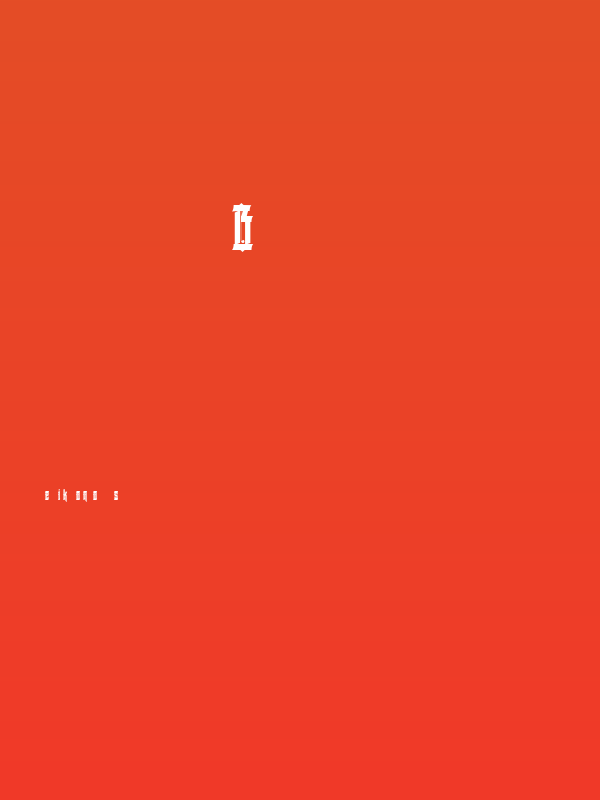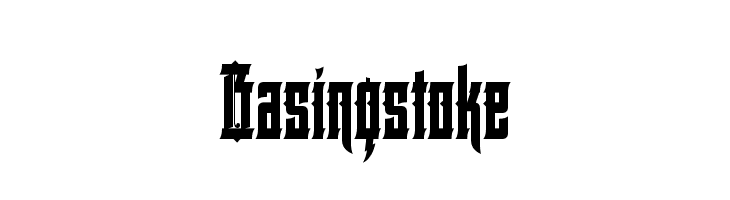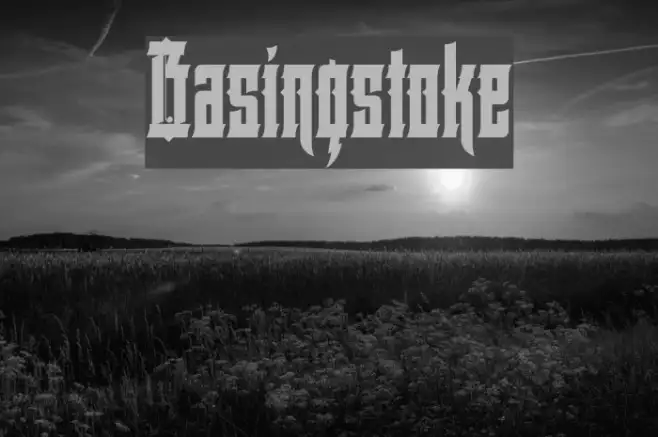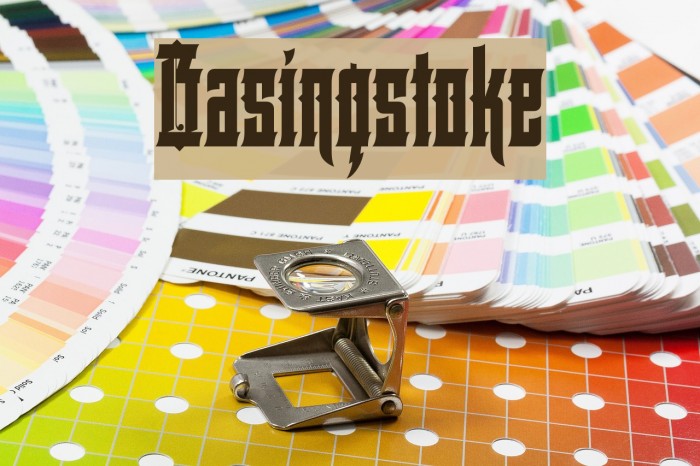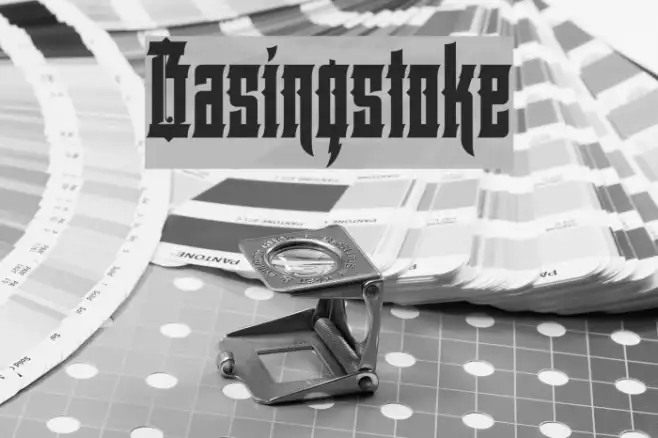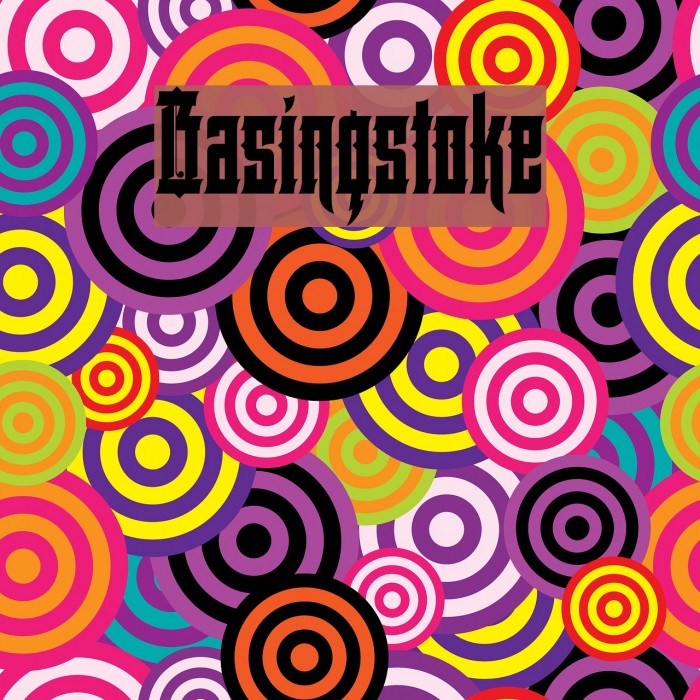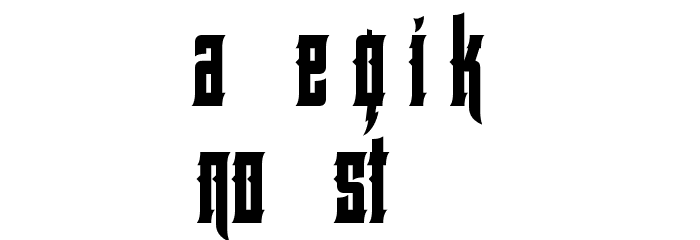
Basingstoke Font
✎ Gothic
| Projets proposés | Ideal for projects requiring a historical or gothic theme, such as book covers, posters, or branding for events with a medieval or fantasy focus. |